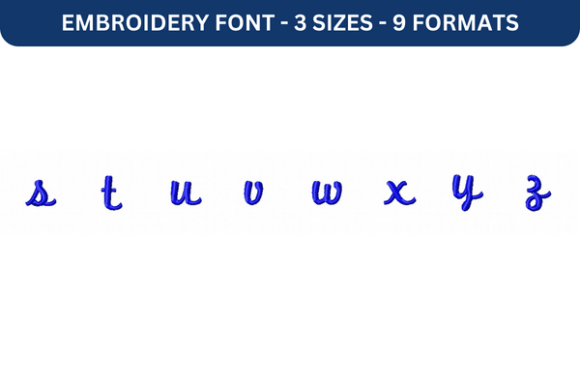
Marketing Script Font Lower S to Z
Jika anda sedang mencari aset berkualiti tinggi seperti Marketing Script Font Lower S to Z, pakej premium ini merupakan pilihan yang hebat untuk projek kreatif anda.
Dicipta dengan ketepatan, Marketing Script Font Lower S to Z menyediakan vektor yang bersih, tipografi yang licin dan lesen komersial untuk ketenangan fikiran.